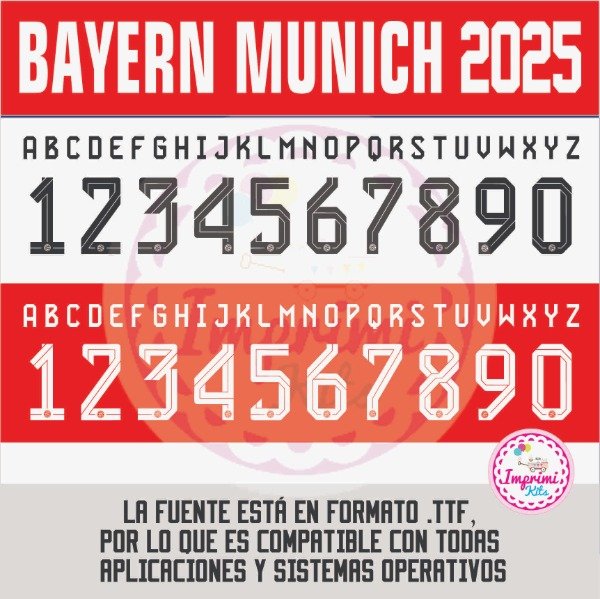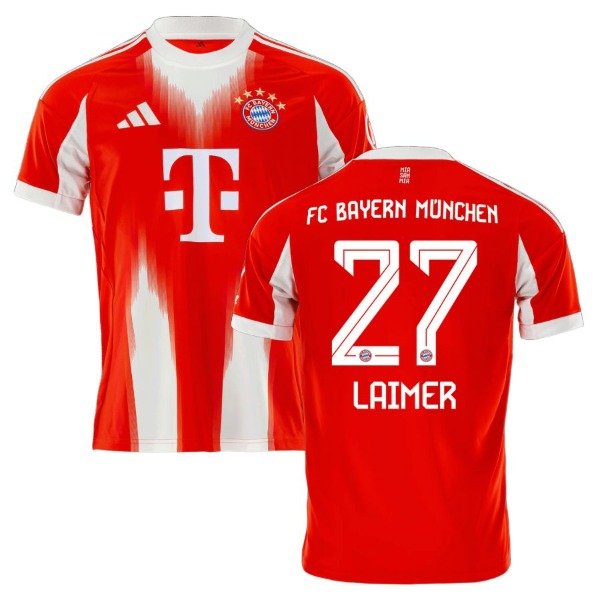
NUEVA! Tipografía Números Fuente Camisetas 2025 2026
BAYERN MUNICH
Tipografía Números Fuente 2025 NUEVAS EQUIPACIÓNES
-La tipografia PARA INSTALAR ES TAL CUAL SE VE EN LA PRIMER IMAGEN
Los vectores de numeros dorsales incluyen detalles y el logo oficial en el numero